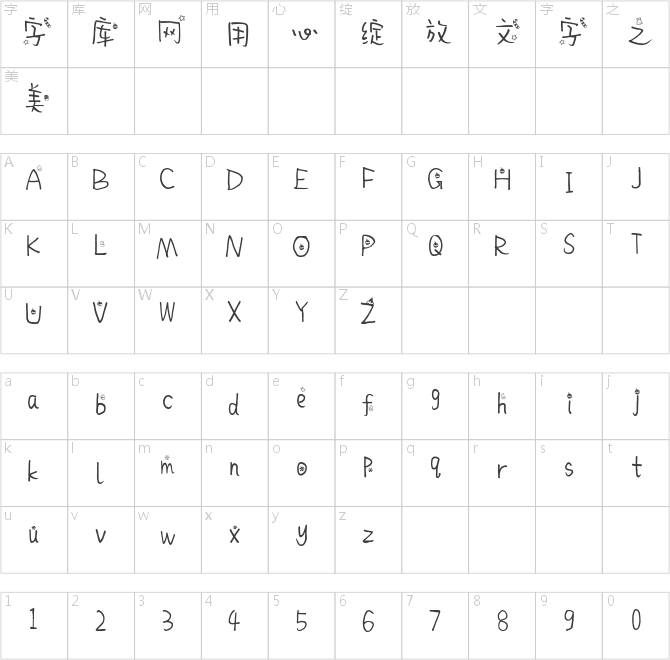
字體名稱: 也字工廠圣誕快
也字工廠圣誕快樂
也字工廠圣誕快樂字體字庫(kù)是一款讓人賞心悅目、百看不厭的中文字體,適合各類廣告和產(chǎn)品包裝設(shè)計(jì)應(yīng)用,字體大小14.86MB,格式為ttf字體,上傳用戶是也字工廠YEFONT,作者/版權(quán)方為也字工廠